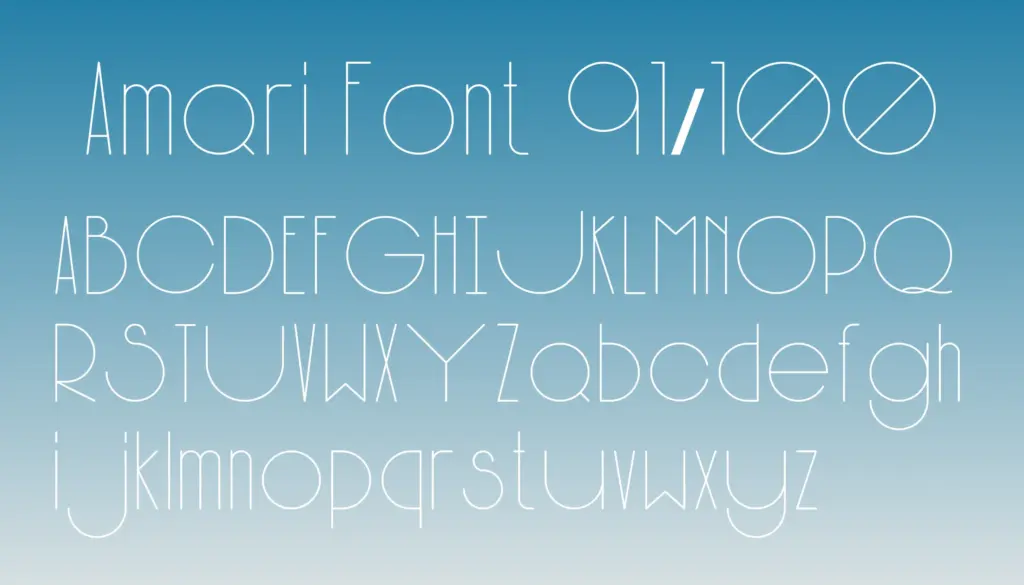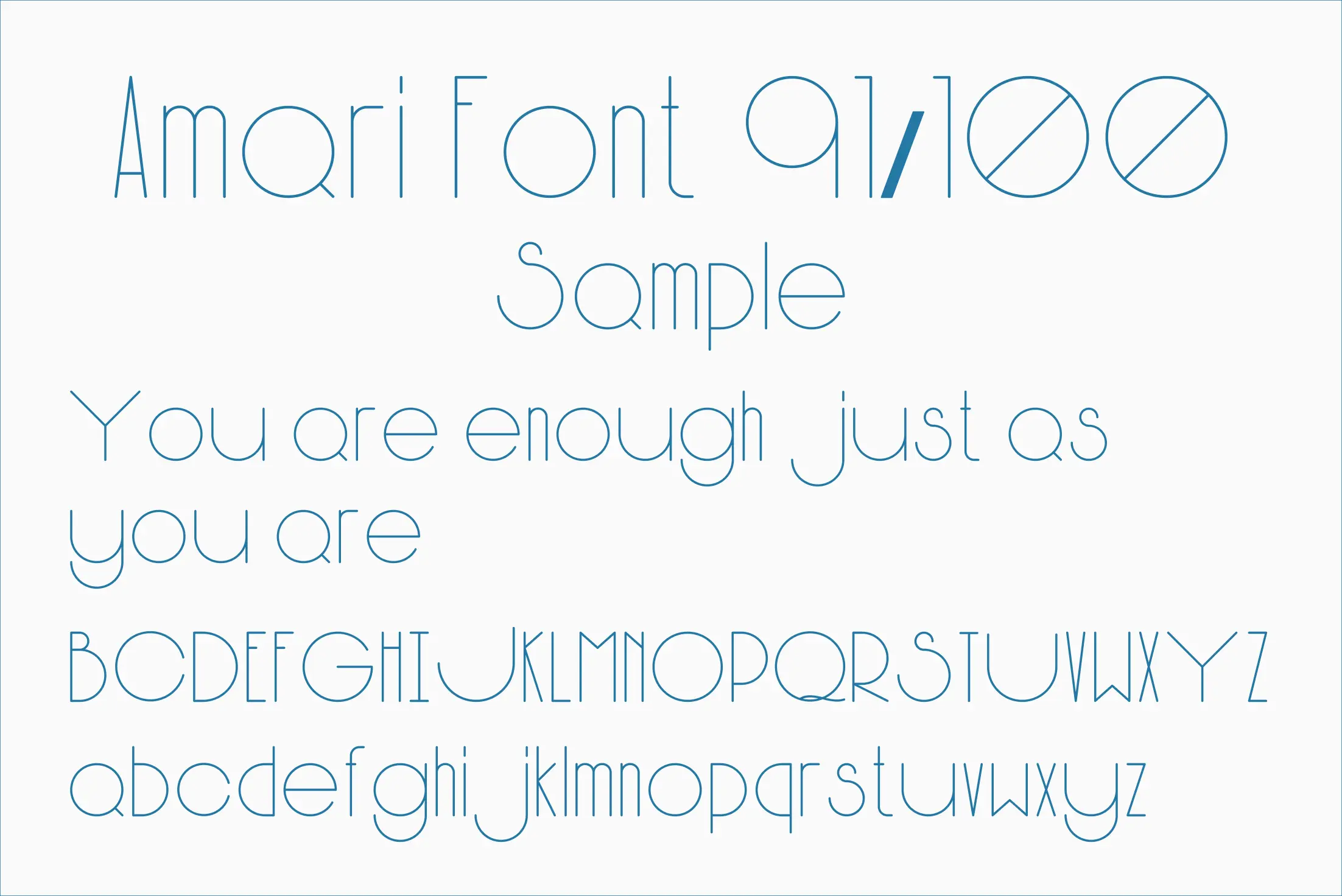
細く洗練されたラインで構成された極細・幾何学的な英字フォントです。文字ごとに個性あるアレンジが施されており、モード感・洗練・静寂を感じさせる美しいデザインが魅力です。ファッション、アート、ビジュアル寄りの高級感のあるロゴ・装飾文字・写真上のタイポグラフィなどに最適です。
Amari Font 91/100